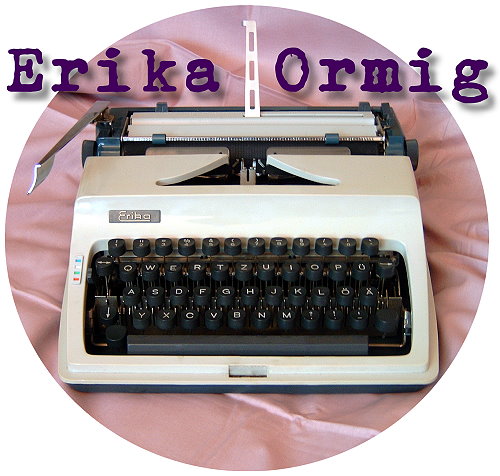
Suche monospaced font für Print
ich bin auf der Suche nach einer monospaced font für ein print Projekt. Die Schrift sollte sehr gut lesbar sein. Mein Problem mit bisherig verwendeten monospaced Schriften, ist dass diese recht "löchrig" wirken. Hat jemand eine Idee, oder einen Schriftvorschlag, der an eine monospaced erinnert?
Was ist denn löchrig für Dich? Monospaced ist ja definiert dadurch, dass der Kegel immer gleich bleibt, egal wie breit der Buchstabe ist, wenn ich mich recht entsinne.
Ansonsten werfe ich die Pragmata ins Rennen.
Die Hellschreiber gefällt mir ganz gut, eine moderne Interpretation einer Schreibmaschinenschrift. Gibt es die auch in einem Schnitt zum testen? Mit löchrig meine ich, dass der Grauwert im Vergleich zu einer Times recht gering ist.
Vielleicht ja auch diese:
Dunkler als Courier New, und mit einer echten Kursiven nach real-schreibmaschinlichem Vorbild.
Wenn die Schrift nur an eine Monospace erinnern soll, würde ich mich mal im Slabserif-Bereich umsehen nach einer quasi proportionalen Schreibmaschinenschrift...
noch ein schritt zurück: warum überhaupt eine monospaced, was sind die gründe?
Gründe für eine monospaced sind, dass die Seiten etwas an eine Akte erinnern sollen.